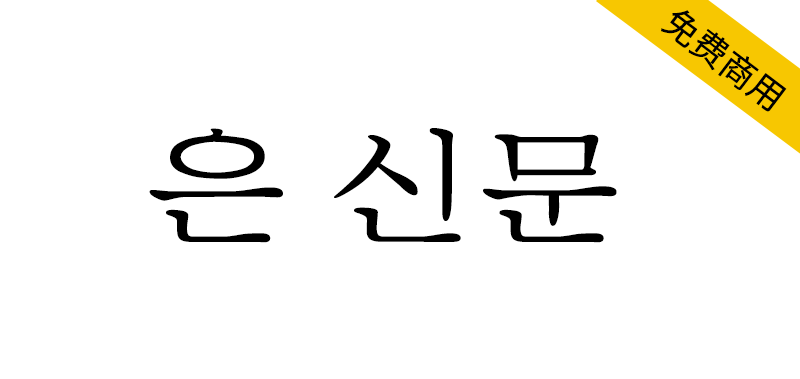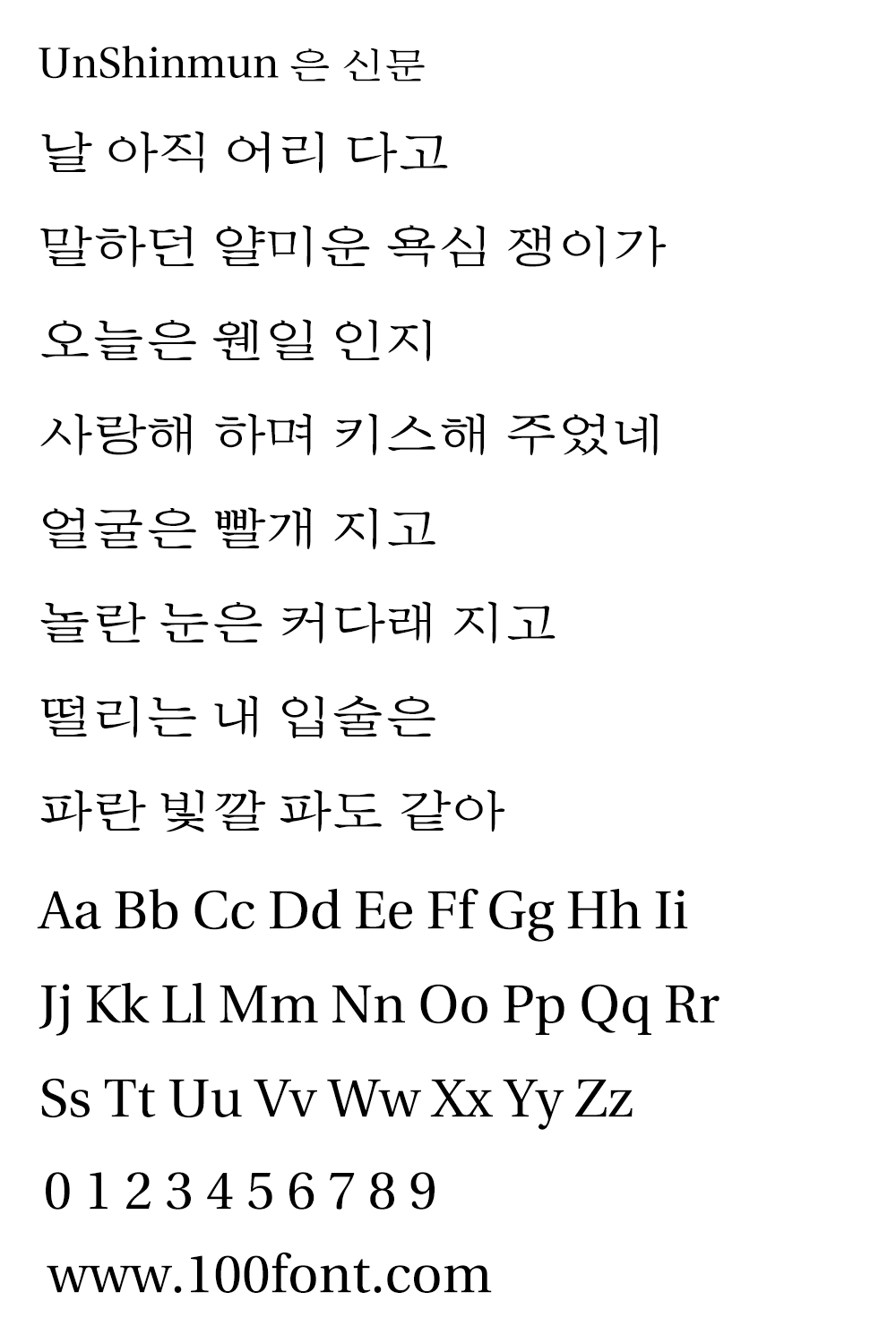
UnShinmun报宋(은 신문)是韩国Un开源系列字体中的其中一款,韩国Un系列字体是由@Koaunghi Un于1998年以HLaTeX type1制作而成,作者在20世纪90年代末制作type1字体用于韩国的Tex(JLaTex[1]),并以GNU GENERAL PUBLIC LICENSE授权许可进行发布。于2003年,由@Won-kyu Park使用FontForge(PfaEdit)转换成ttf文件进行发布。
注意:这款字体支持的简体中文字数比较少,不适用用于简体中文场景,适用于韩语和繁体。